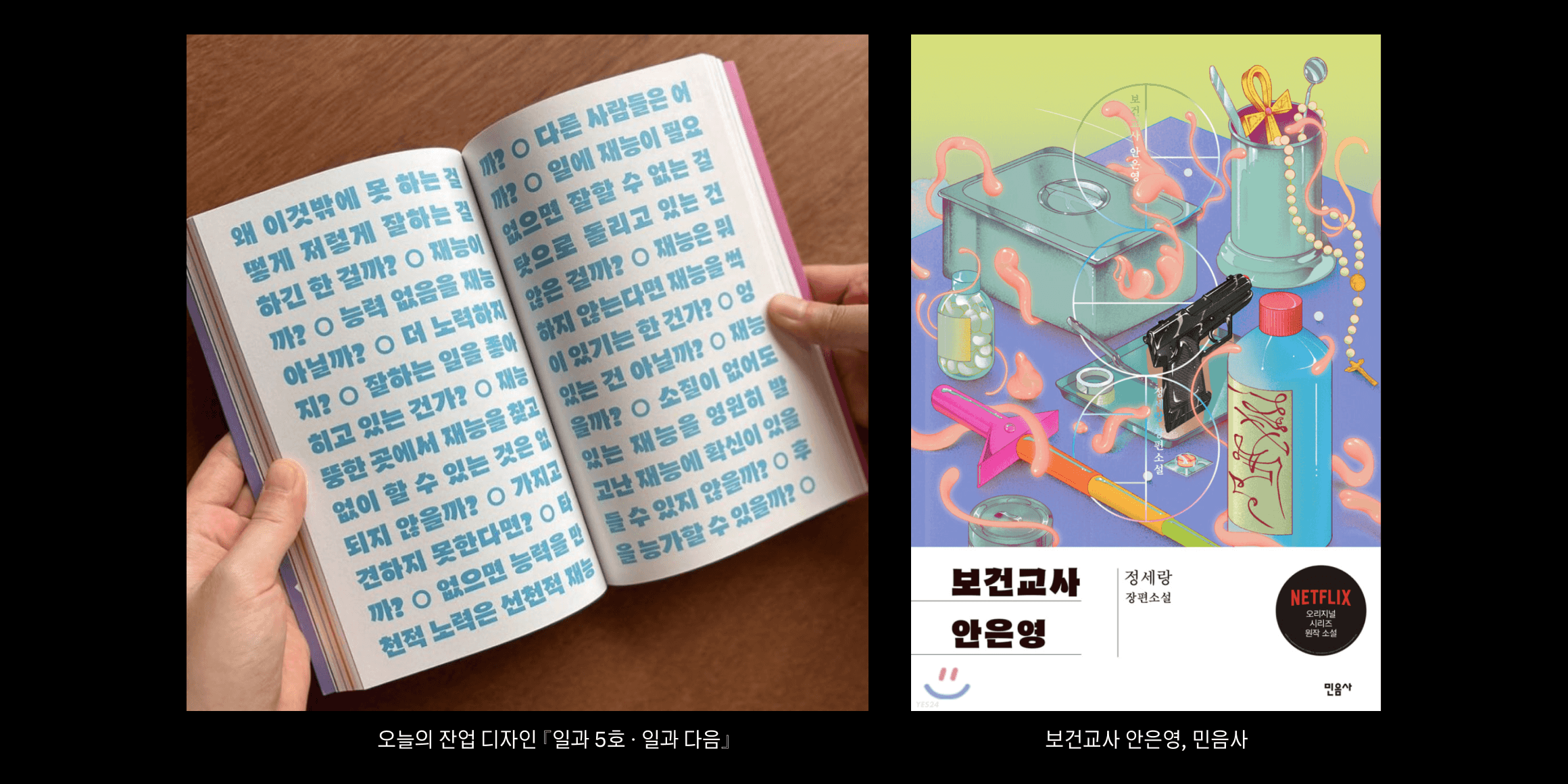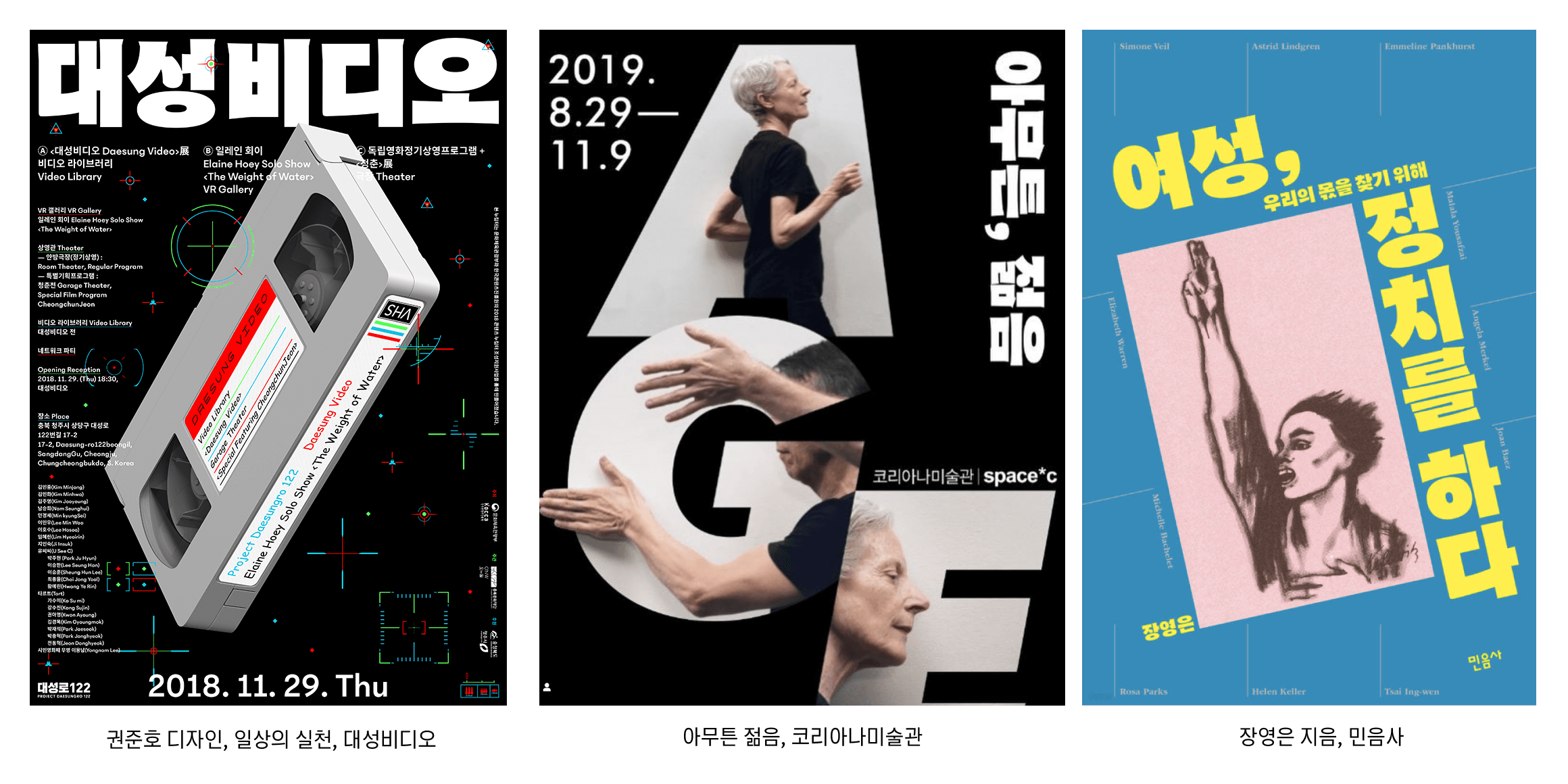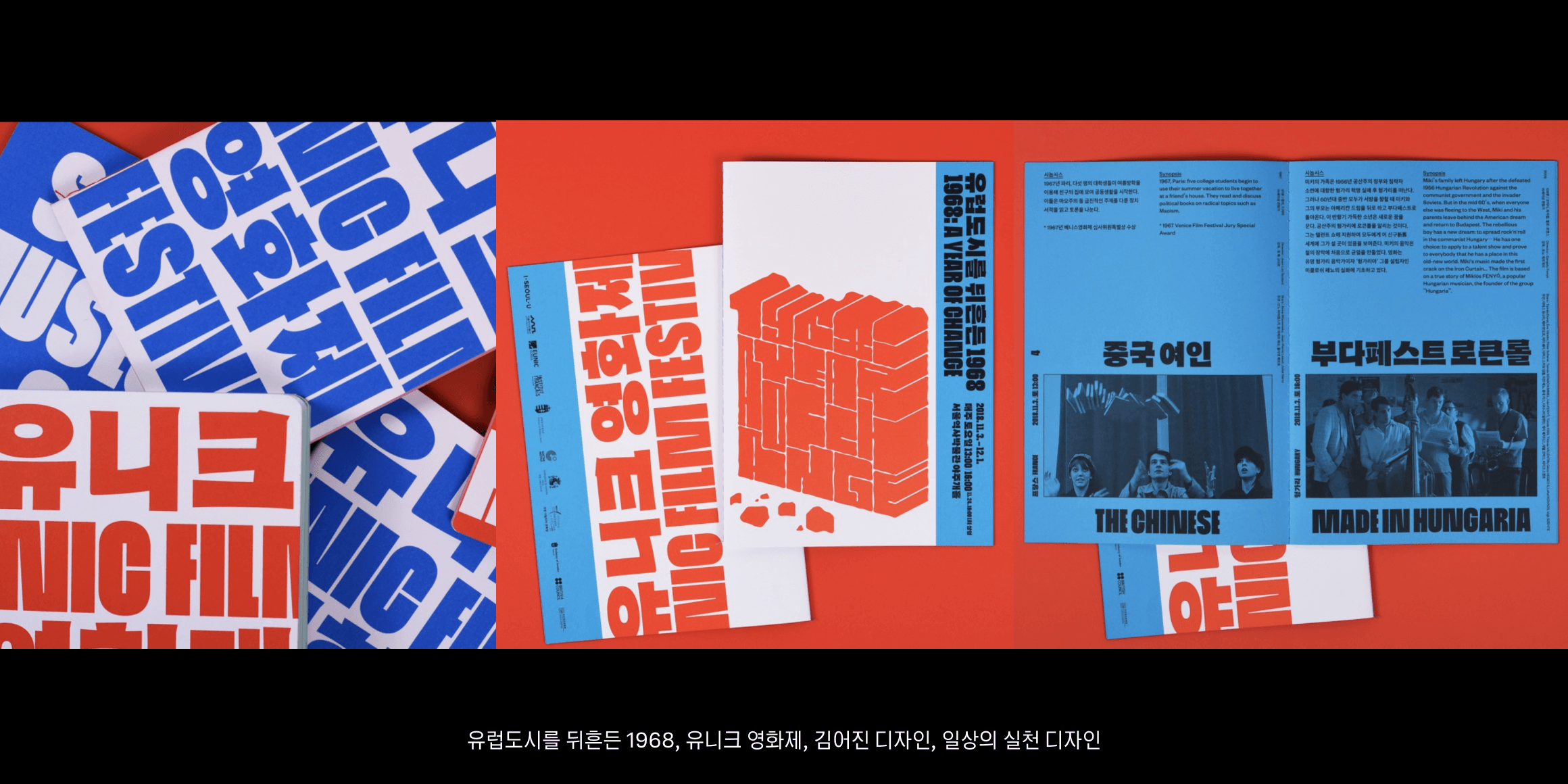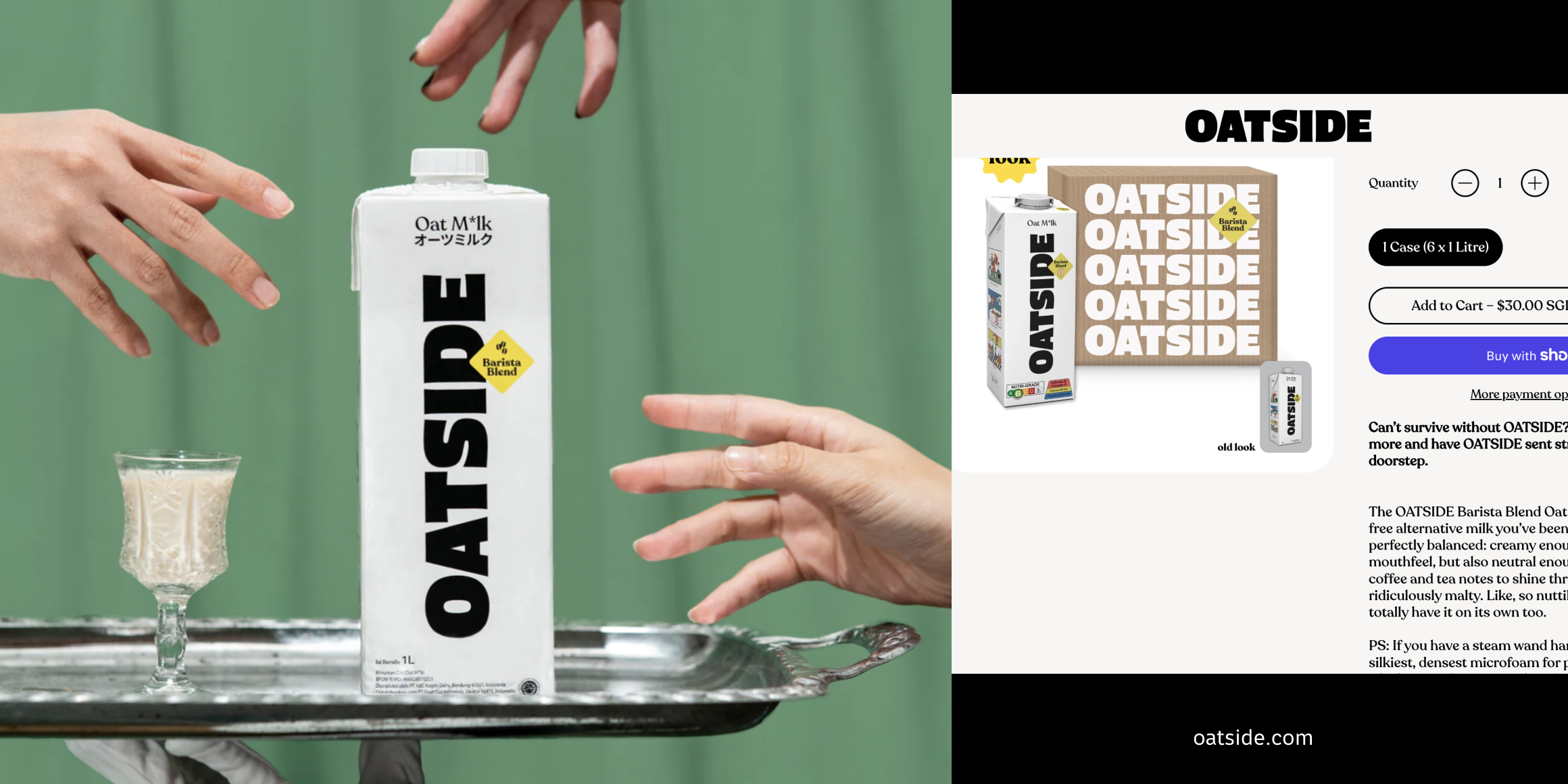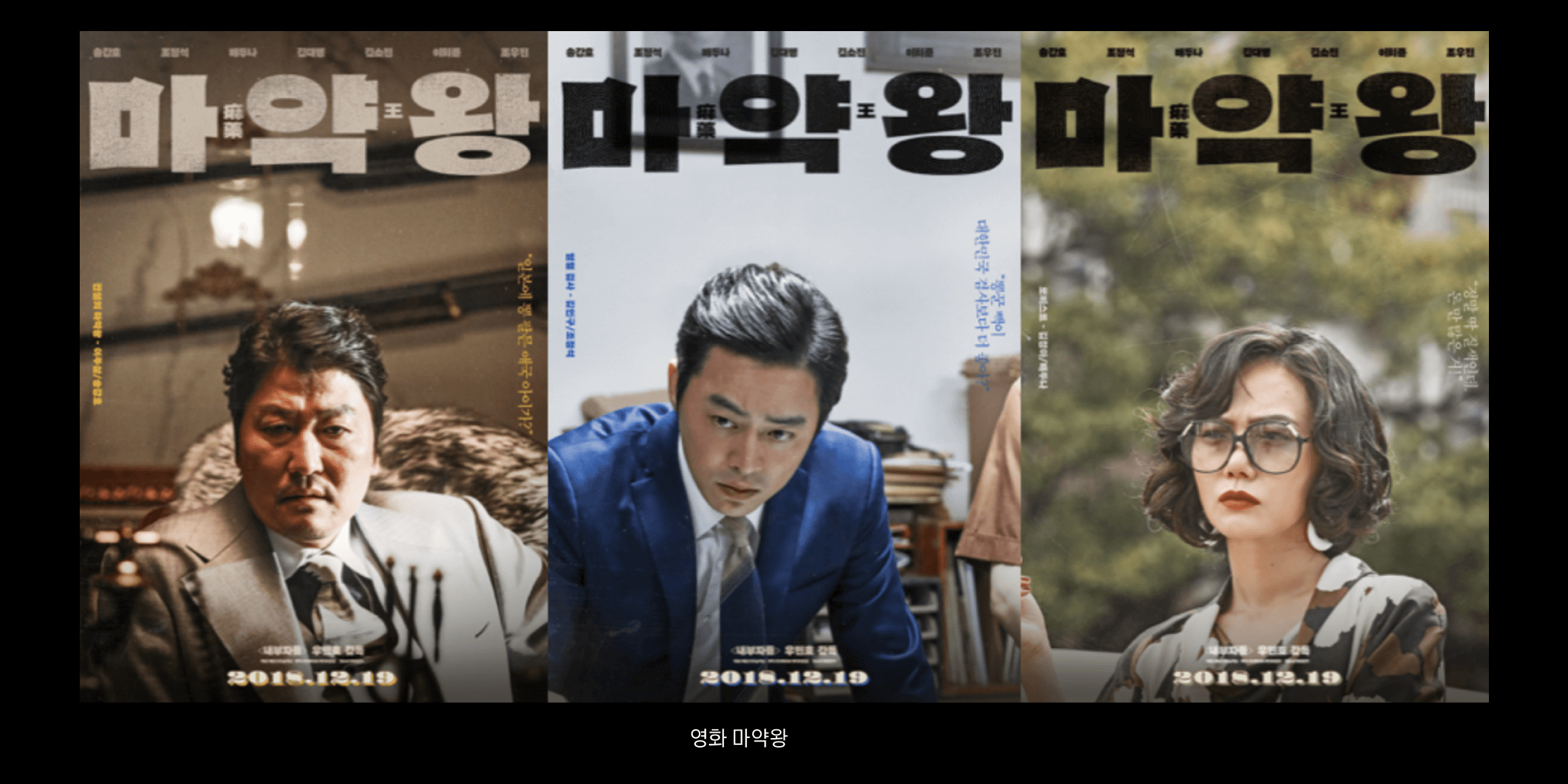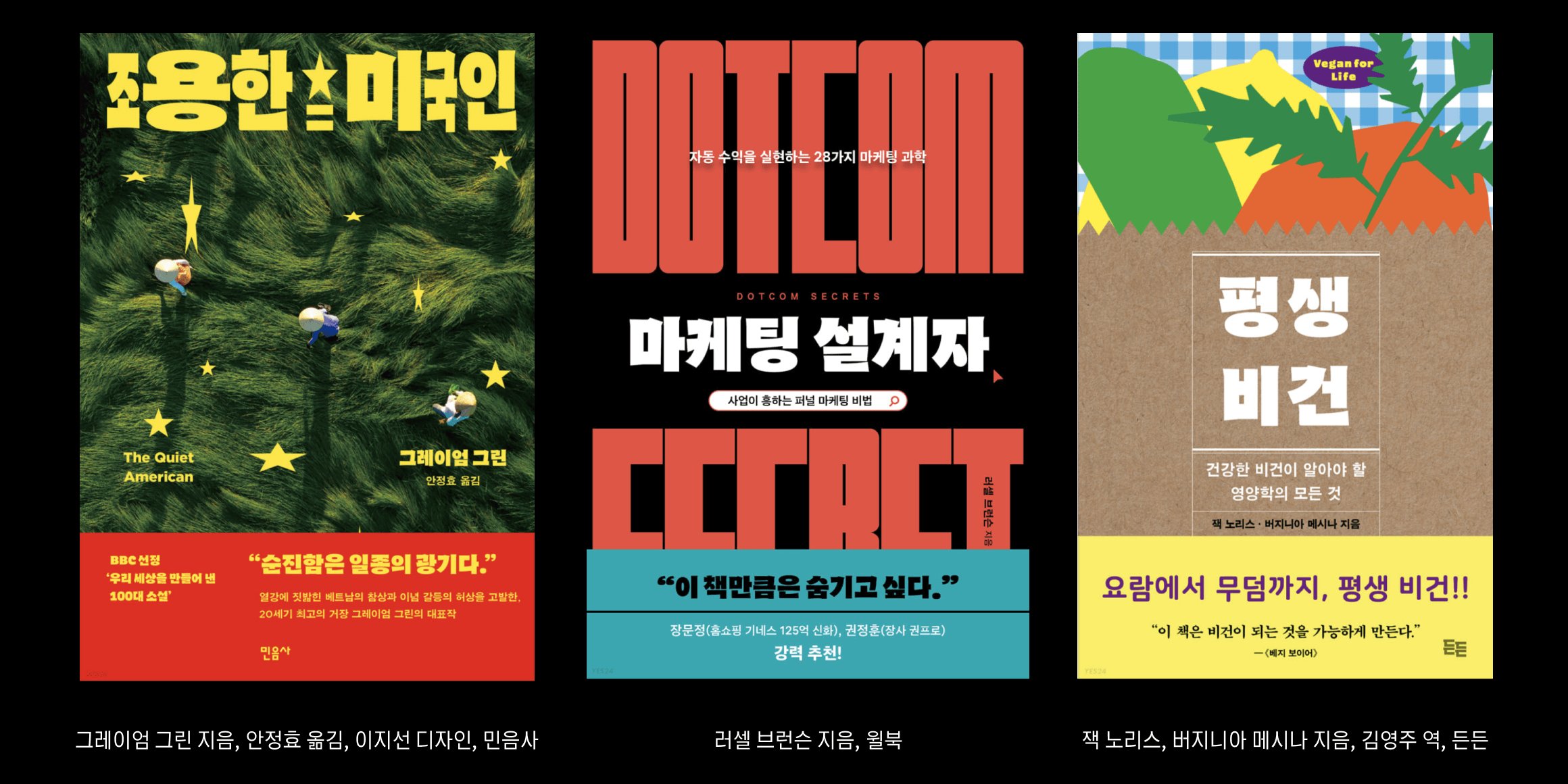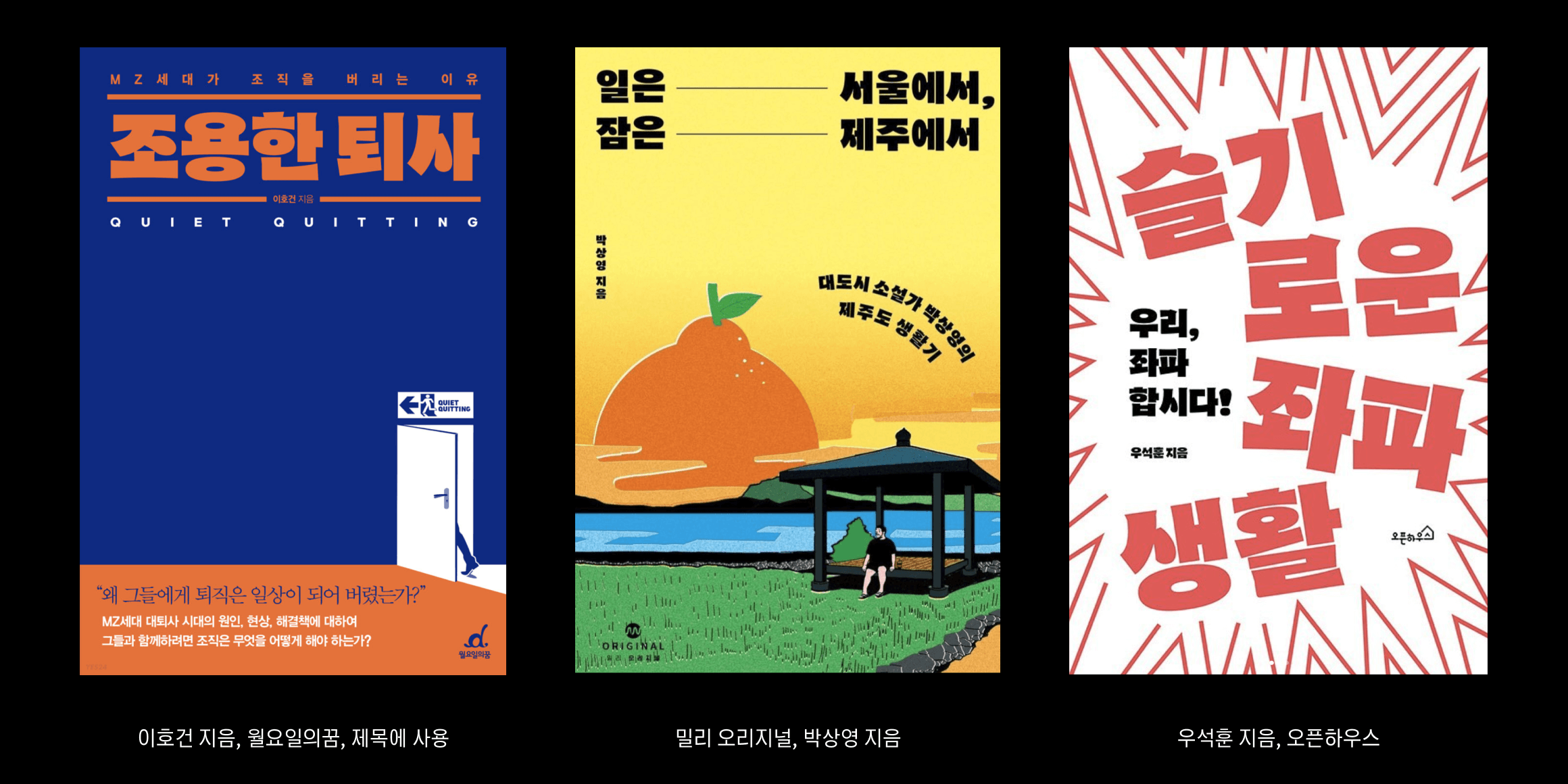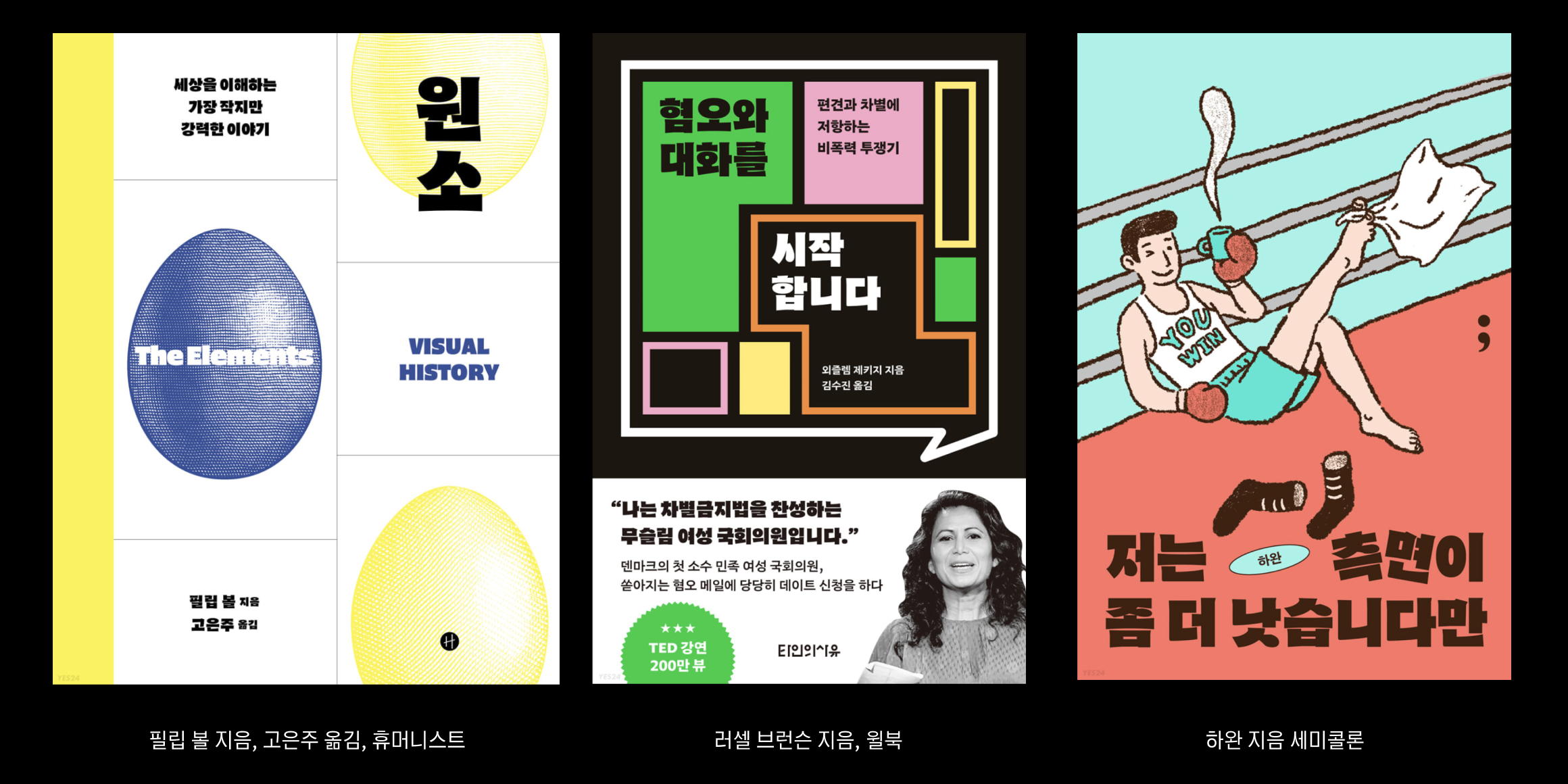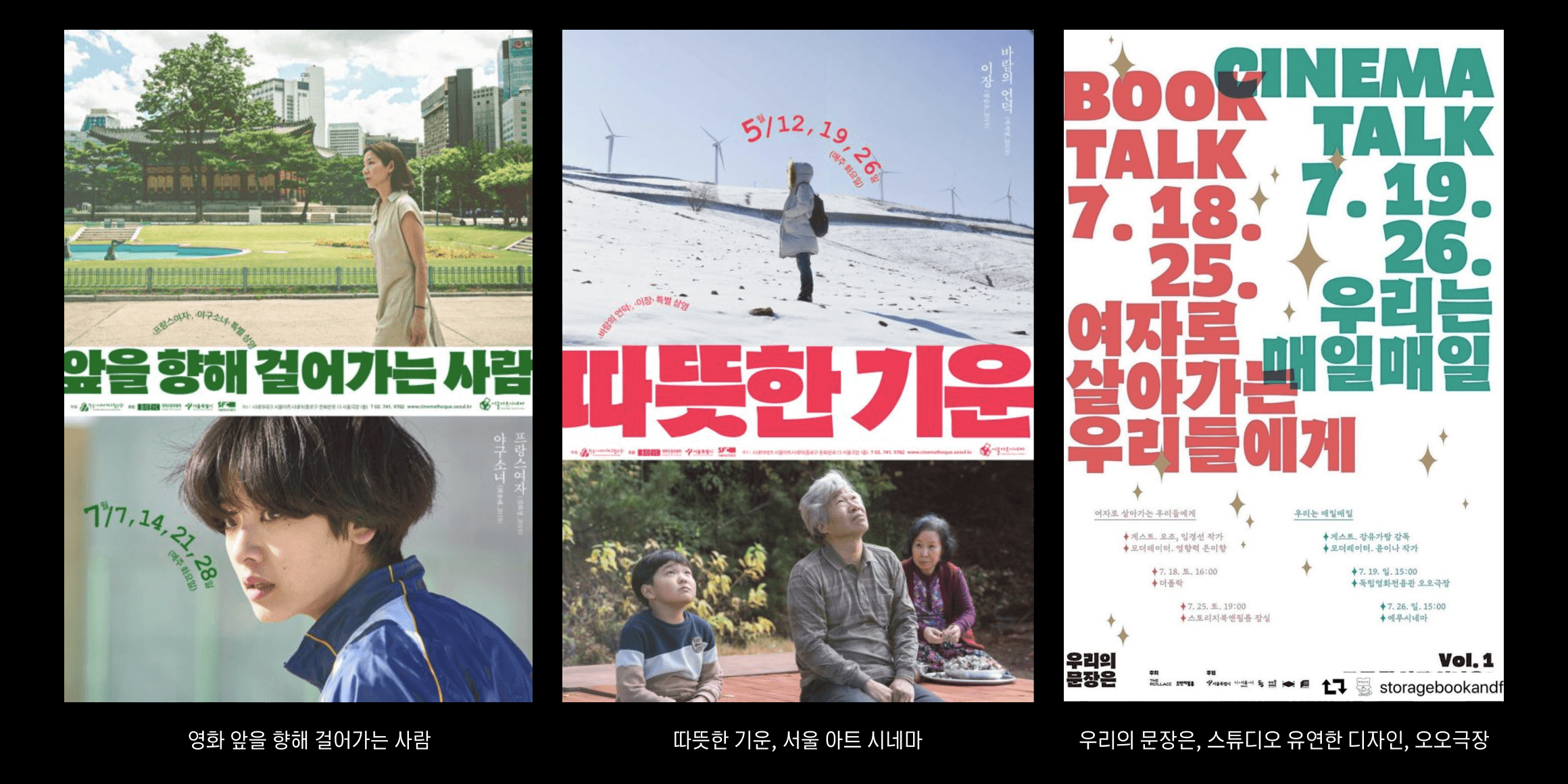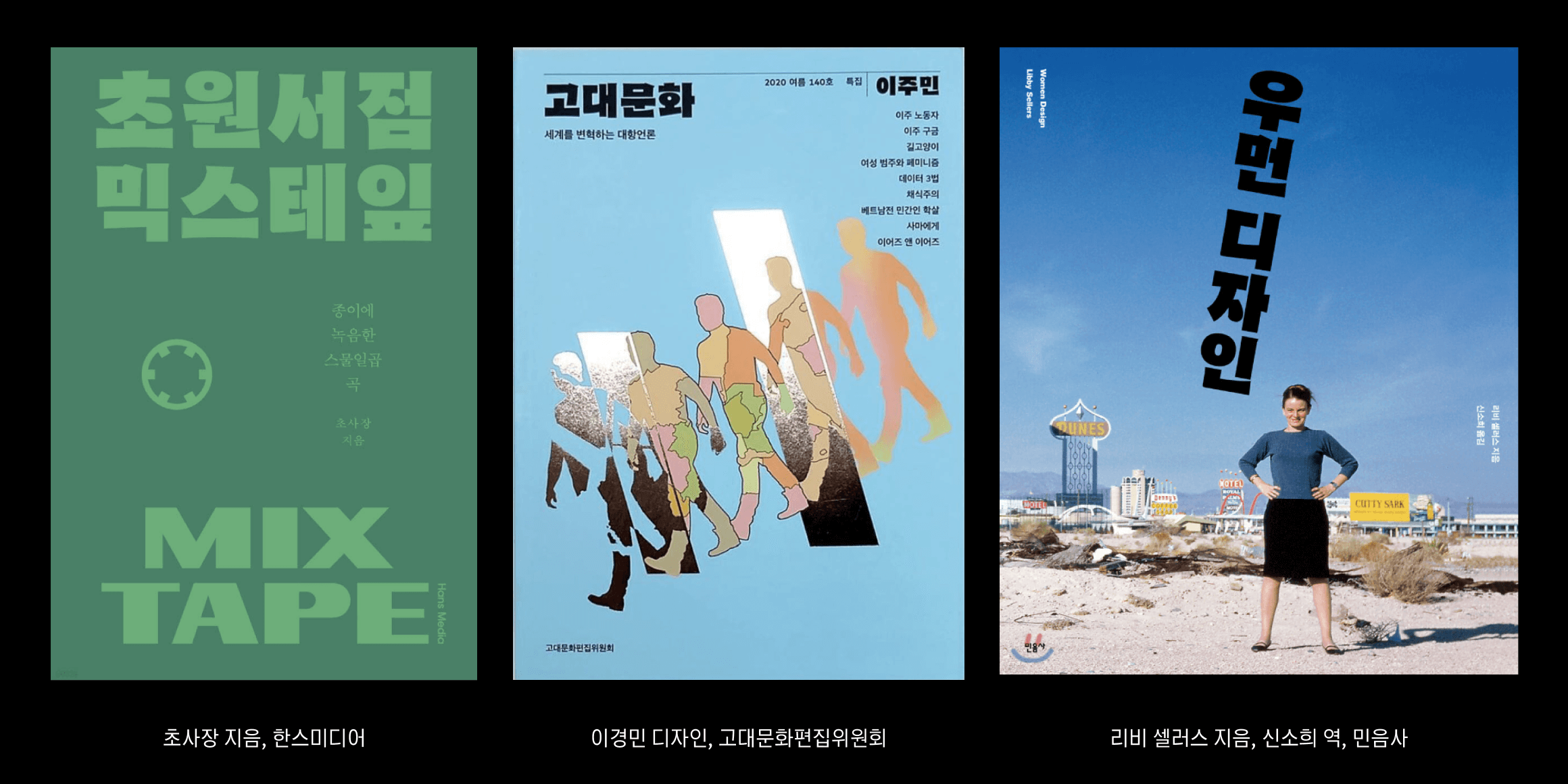
1940년대 영화 포스터의 제목 레터링에서 영감을 얻었습니다. 아주 굵은 한글 폰트를 그려보고자 원래 영감을 받은 글자보다 조금 더 두껍게 살을 붙이고 현대적인 느낌으로 다듬어 나온 결과물 입니다.
롯데리아 광고
<사고는 없다 - 김승진> 북커버
<과학 재판을 시작합니다 - 양지열> 북커버